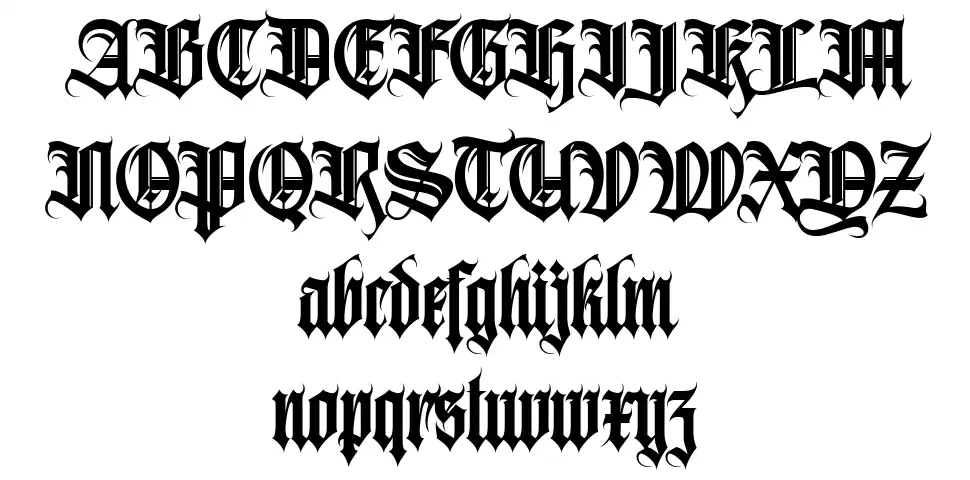
38 Tattoo Schriftart
Fortunately we have many unique tattoo font styles for men and women such as calligraphy cursive and traditional styles. Egal ob sie sich einen namen ein lebensmotto oder inspirierendes zitat stechen lassen ist die schriftart von zentraler bedeutung. Die schriftarten für tattoos sind zahlreich und deshalb fällt die entscheidung für die passende schrift manchmal schwer.